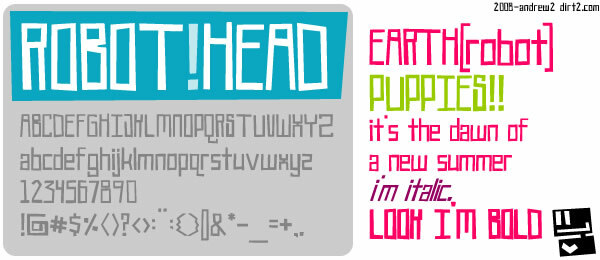
Robot!Head to darmowy, komiksowo-techno font typu display, który sprawia wrażenie robota wykonanego w domowych warunkach. Litery są wysokie, kanciaste i celowo nieco niezdarne; połączenie wąskich pionowych kresek, kwadratowych łuków i nierównych poprzeczek nadaje całemu krojowi bardziej zabawny niż wygładzony charakter.
Świetnie sprawdzi się na plakatach, w logach gier, na okładkach zinów, naklejkach i opakowaniach, które potrzebują prostego, sci-fi klimatu zamiast surowego futuryzmu. Jako darmowy font, najlepiej sprawdza się w krótkich słowach i nagłówkach, gdzie te niestandardowe, prostokątne formy i specyficzny rytm mają przestrzeń, by wybrzmieć.